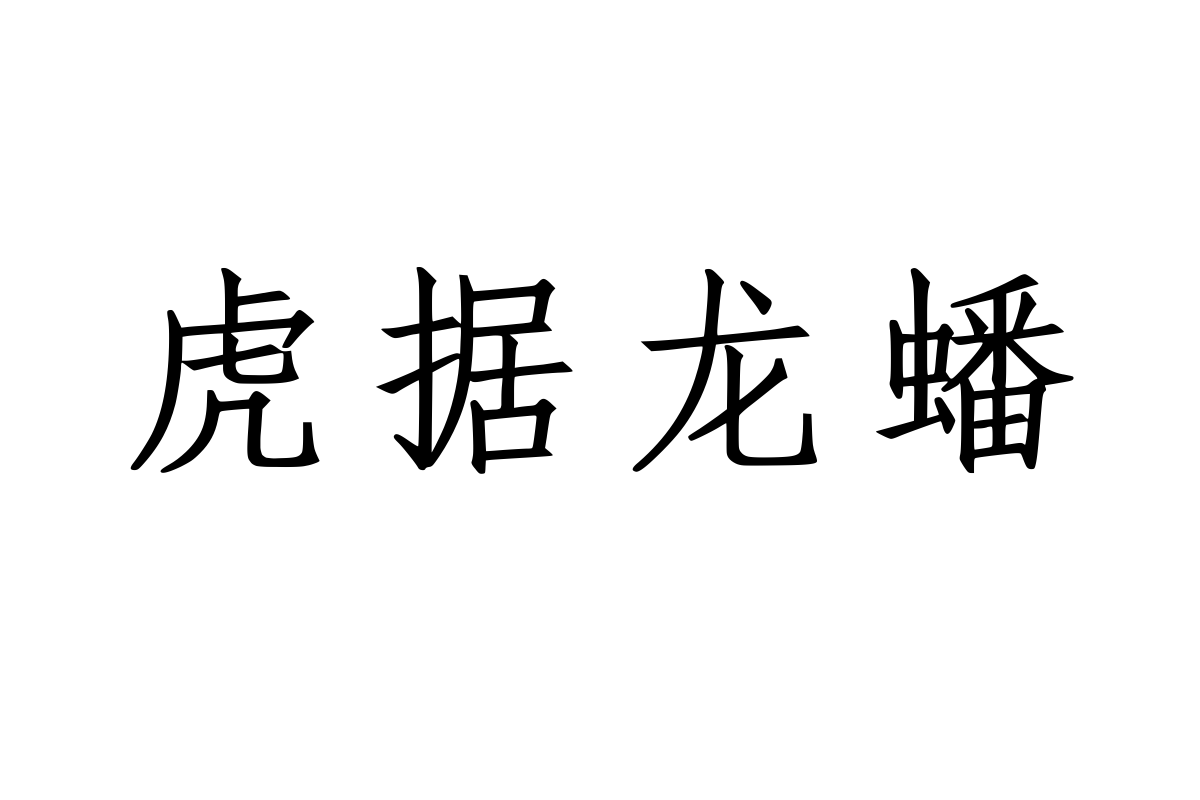
兰米雅宋字体是一款具有独特魅力的中文字体,它由北京兰米雅科技有限公司设计并开发。这款字体以其优雅而独特的风格,深受广大设计师和用户的喜爱。
兰米雅宋字体的特点主要表现在以下几个方面:
1. 字形优美:兰米雅宋字体采用了传统的书法笔触,使得每个字都显得圆润饱满,线条流畅自然。这种优美的字形不仅能够提升整体的设计效果,还能够使文字更具艺术感。
2. 风格独特:兰米雅宋字体在保持传统书法韵味的同时,还融入了一些现代元素,使其既有古典之美,又不失时尚感。这使得兰米雅宋字体在各类设计作品中都能展现出独特的魅力。
3. 适用范围广泛:兰米雅宋字体适用于各种类型的设计作品,如海报、宣传册、网页等。无论是商业广告还是文化传播,兰米雅宋字体都能够为设计作品增添一份独特的美感。
4. 易于使用:兰米雅宋字体采用矢量化设计,可以方便地在不同尺寸和分辨率下保持字体的清晰度和可读性。这使得设计师在使用时更加便捷,无需担心因字体大小变化而导致的视觉问题。
总之,兰米雅宋字体是一款具有独特魅力的中文字体,它以其优美的字形、独特的风格、广泛的适用性和便捷的使用方式,赢得了广大设计师和用户的青睐。